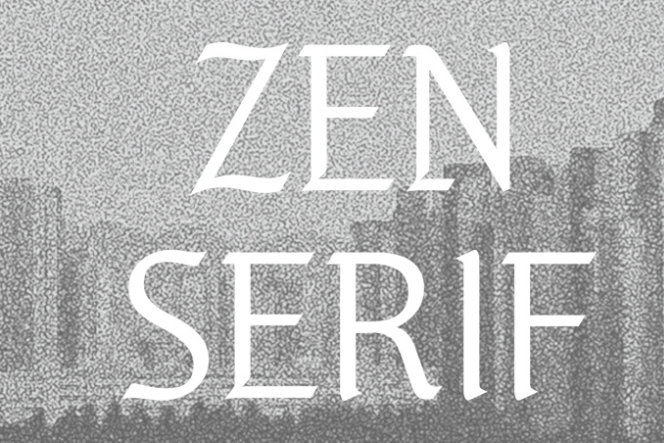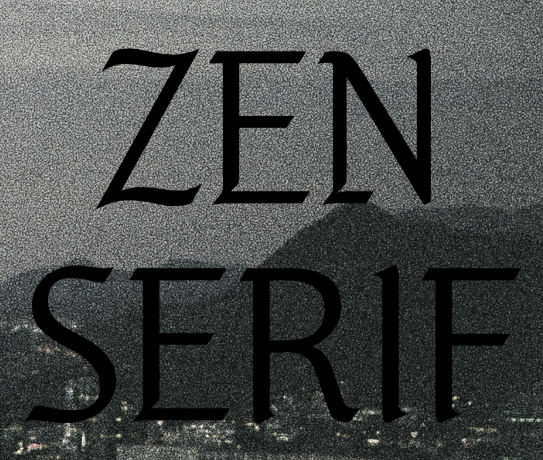
한글날을 맞아 블랙핑크 제니가 소속사 OA엔터테인먼트(ODDATELIER)를 통해 새로운 한글 폰트 젠 세리프(ZEN SERIF)를 공개했습니다.
전통적인 한글의 미학과 현대적인 세리프 디자인을 결합한 이번 폰트는, 누구나 무료로 다운로드해 사용할 수 있는 공개 서체로 주목받고 있습니다. 특히 세련된 곡선과 깔끔한 자형 덕분에 블로그, 디자인, 인쇄물 등 다양한 콘텐츠에 활용 가능한 고급 한글 폰트로 평가받고 있습니다.
제니가 한글날에 선보인 젠 세리프(ZEN SERIF)는 OA엔터테인먼트 공식 홈페이지에서 무료로 배포되고 있으며, 감각적인 세리프 구조와 높은 가독성으로 국내외 사용자들 사이에서 큰 화제를 모으고 있습니다.
1. 제니 한글 폰트, 젠 세리프란?
젠 세리프(ZEN SERIF)는 제니와 OA엔터테인먼트가 함께 만든 현대적 감각의 세리프형 한글 글꼴입니다. 전통적인 서양의 블랙레터 스타일에 한글 고유의 자형 미를 결합해, 한국적이면서도 글로벌한 감성을 담았습니다.
- 제작: OA엔터테인먼트 (ODDATELIER)
- 특징: 장식 최소화, 곡선형 세리프 구조, 한글·영문 통합 디자인
- 제니가 직접 참여한 글로벌 한글 서체 프로젝트.
- ‘ZEN SERIF’는 전통과 현대미를 결합한 세리프 글꼴.
3. OA엔터테인먼트의 제작 배경
OA엔터테인먼트는 젠 세리프를 “누구나 한글을 편리하고 아름답게 사용할 수 있도록 하려는 제니의 바람에서 출발했다”고 밝혔습니다.
한글날의 의미를 현대적으로 재해석하며, 제니는 “세종대왕의 창제 정신을 이어 한글의 미학을 전 세계에 전하고자 했다”는 메시지를 담았습니다.
- OA엔터는 젠 세리프를 통해 “한글의 단정함과 유연한 곡선을 예술적으로 표현했다”고 설명했습니다.
- 전통적인 미감과 OA엔터테인먼트 특유의 섬세한 감성이 조화된 디자인으로 평가받고 있습니다.
- 한글날을 기념해 공개된 제니의 첫 공식 폰트 프로젝트.
- ‘누구나 쉽게, 아름답게 한글을 쓰자’는 철학을 담고 있음.
- 한글의 전통미와 글로벌 감각의 결합.
4. 젠 세리프 폰트의 디자인 특징
젠 세리프는 장식을 최소화하고 본질을 살린 세리프형 글꼴로, 딱딱한 인상 대신 부드럽고 세련된 곡선을 더했습니다.
1) 고급스러운 세리프 구조
획 끝 부분에 자연스러운 세리프 장식이 있어 문장에 깊이감과 안정감을 줍니다.
2) 부드러운 곡선과 절제된 디테일
불필요한 요소를 제거하고, 글자 간 간격을 균형 있게 조정해 깔끔한 인상을 유지합니다.
3) 한글과 영문의 자연스러운 조화
라틴 알파벳과 한글이 함께 쓰일 때 균형 잡힌 레이아웃을 구현할 수 있도록 설계되었습니다.
- 블랙레터 기반의 새로운 한글 세리프 스타일.
- 장식 최소화, 곡선 강조, 균형 잡힌 자간 구조.
- 한글·영문 조화에 최적화된 통합 서체.
Q2. 제니가 직접 제작에 참여했나요?
A2. 제니는 한글의 미학을 세계에 전하고자 하는 기획 단계에 참여했으며, 디자인은 OA엔터테인먼트의 아트팀이 담당했습니다.
Q3. 영문도 포함되어 있나요?
A3. 네, ZEN SERIF는 한글과 영문을 모두 지원하는 통합 서체입니다.
제니가 만든 한글 폰트 젠 세리프(ZEN SERIF)는 한글날을 기념해 공개된 고급스러운 세리프 서체로, 누구나 무료로 사용할 수 있습니다.
전통과 현대미가 공존하는 이 서체는 ‘한글의 아름다움을 세계에 알리겠다’는 제니의 철학이 담긴 글꼴로, 블로그, 인쇄물, 포스터 등 다양한 콘텐츠에서 돋보이는 결과물을 만들어낼 수 있을 것입니다.